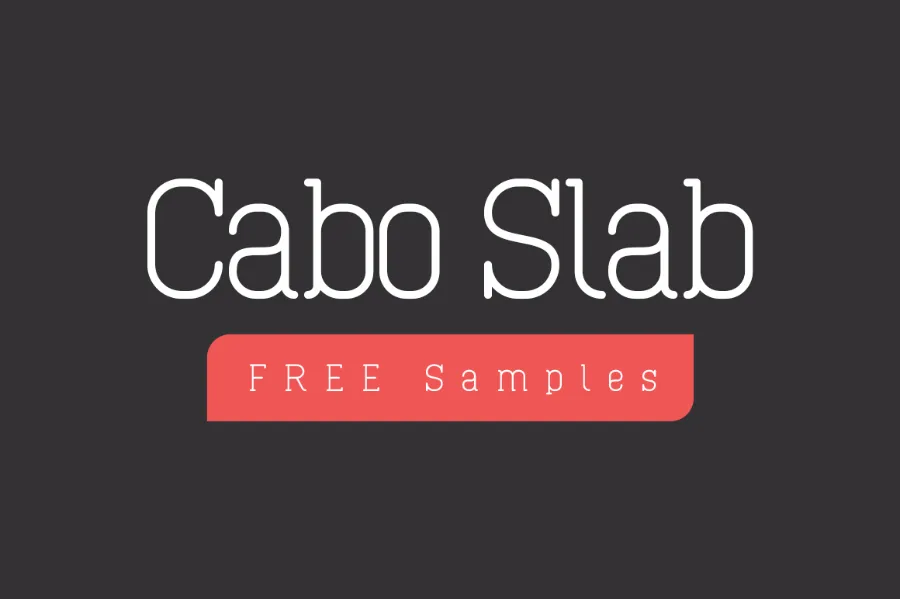
Cabo Slab Font Family – Fonte Grátis
Cabo Slab Font Family
Descubra a novidade no mundo das fóntes com Cabo Slab Font Family, uma família slab serif cuidadosamente projetada por Design a Lot. Fundada na inspiração da versão sans-serif “Cabo Rounded”, essa nova família de fôrtes letras contém sete pesos e quatorze estilos, incluindo todas as letras básicas do alfabeto, sinais de pontuação e alguns acréscimos. Este conjunto de fontes, ideal para uma ampla variedade de aplicações, oferece um toque de modernidade com o charme sofisticado da serif. Com Cabo Slab Font Family, você encontra a perfeita combinação entre força visual e elegância tipográfica. Seja em design gráfico, publicidade ou qualquer projeto que exija uma fonte robusta e reconhecível, essa família de fóntes é sua escolha natural.